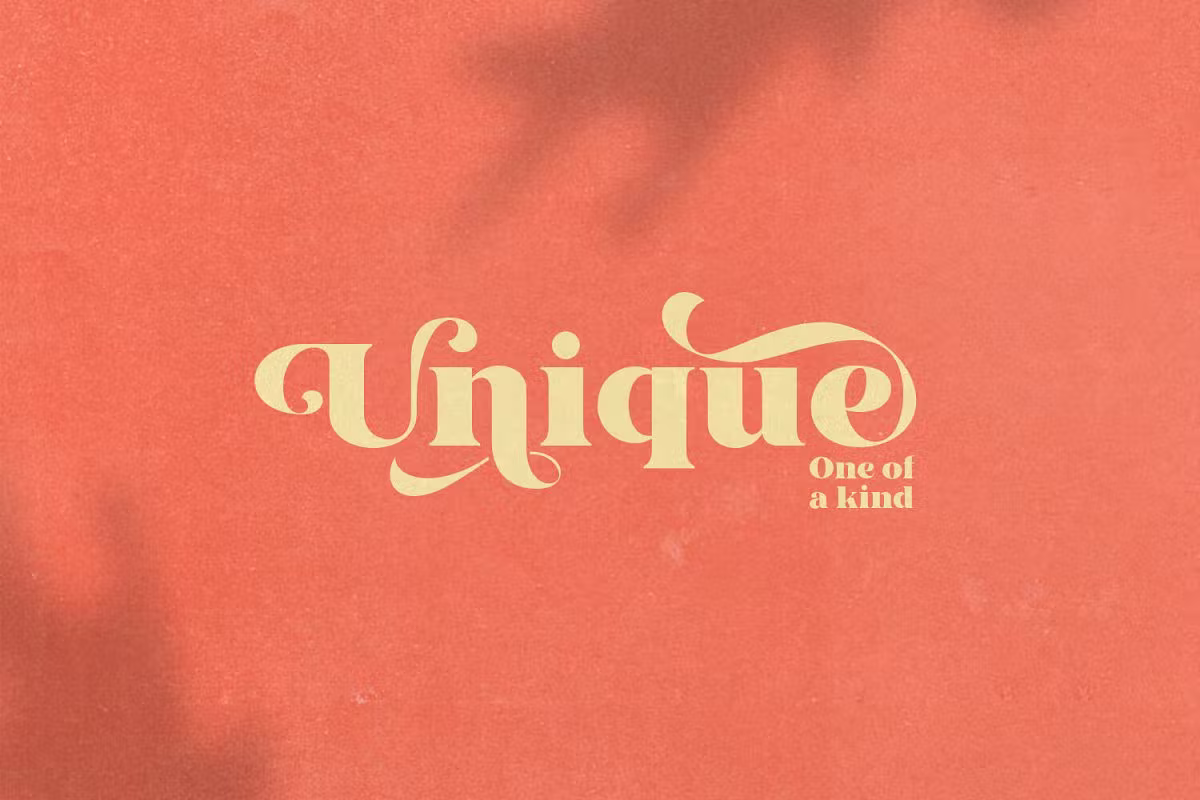
Kaoly Font
Description de Kaoly Font
Kaoly Font Serif gras unique avec de nombreux caractères alternatifs uniques et magnifiques que vous pouvez combiner pour obtenir un beau lettrage final avec des formes agréables et dynamiques en quelques secondes seulement ! Merci pour les alternatives uniques !
Ceci est la version allégée pour ce style, change uniquement en majuscules, nous avons également supprimé les lettres alternatives pour réduire la taille du fichier, elle chargera beaucoup plus rapidement votre site Web lorsque vous utilisez cette police pour le texte d’en-tête du site Web, le titre des produits ou en utilisant applications qui ne prennent pas en charge les fonctionnalités OpenType, il est très facile de créer de beaux mots simplement en tapant et tada… vous avez terminé.
Kaoly rendra votre travail facile et amusant.